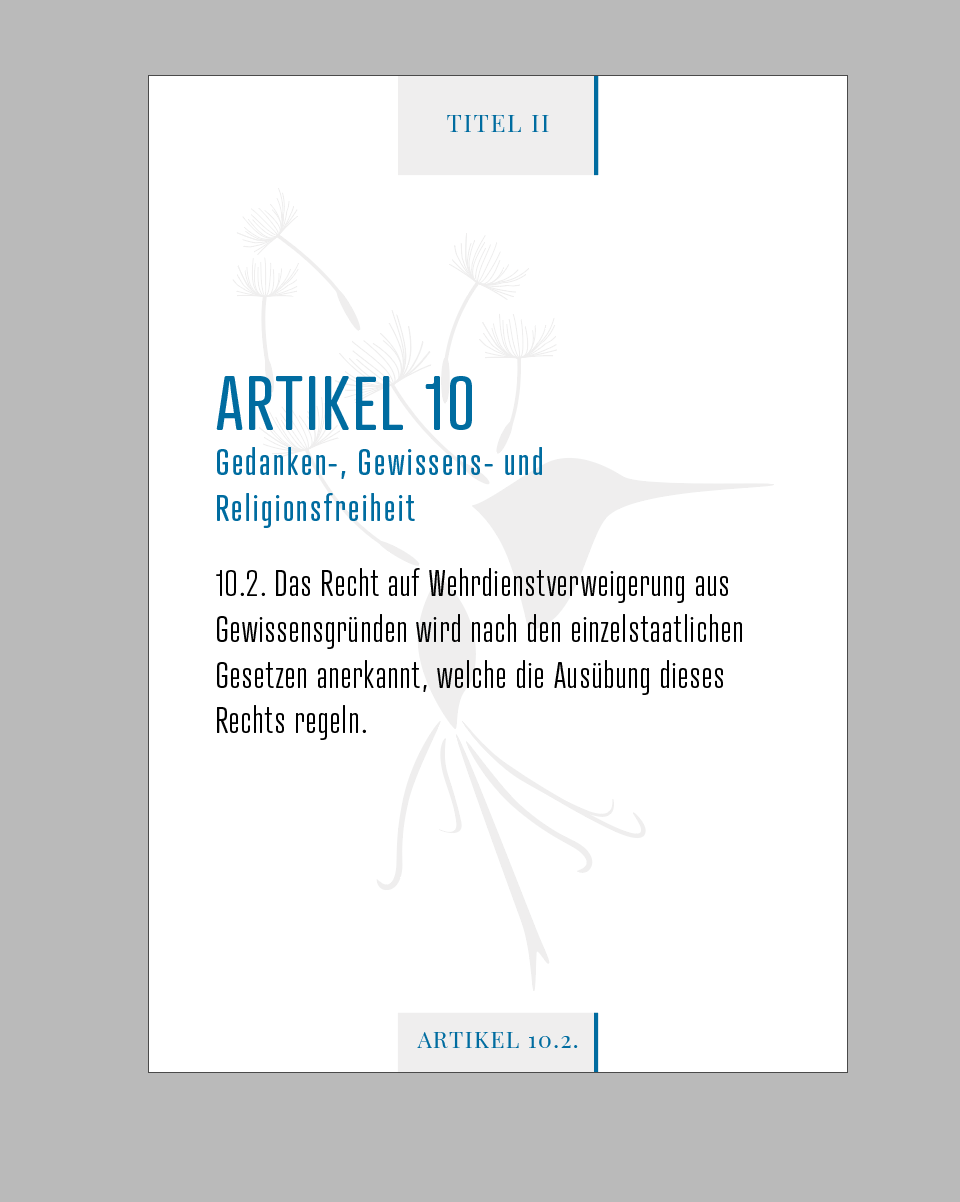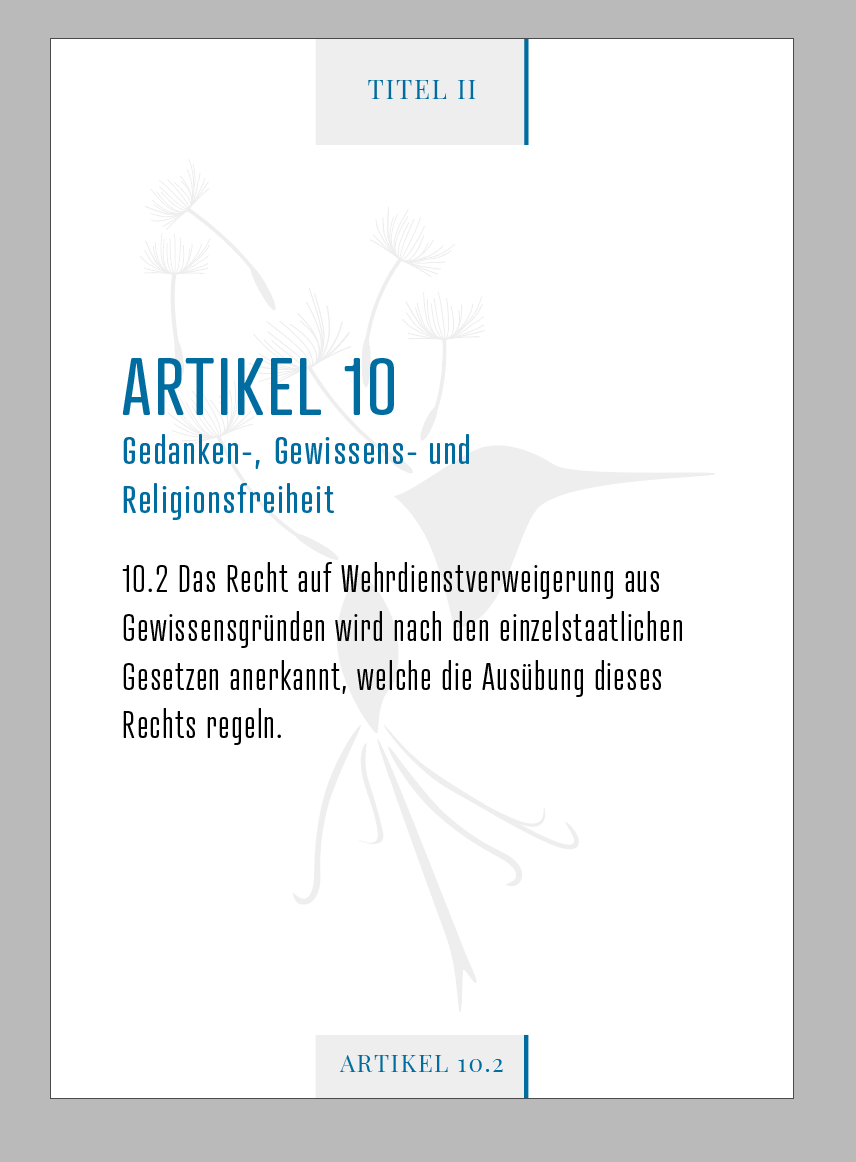
Fonts die miteinander Harmonieren / alle 27 EU Länder beinhalten
dürfte ich euch um Rat bitten. Ich suche zwei Fonts die nicht nur miteinander Harmonieren (Headline, Subline, Fließtext, Fusszeile,) inkl. gute Lesbarkeit (21, 10, 6 Punkt) besitzen, sondern alle Zeichen/Sprachunterstützung der 27 EU-Mitglieder/Länder beinhaltet bzw. unterstützen.
Zielgruppe: Kinder, Jugendliche, Pädagogen, Studenten, Professoren, Sozial-Einrichtungen
Thema: Menschen, Sozial, Politisch, Rechte
Ich finde die größte Herausforderung ist Schriften zu finden, die alle 27 EU-Länder beinhalten.
Diverse Schriftvertriebe haben Standards entwickelt, um in ihren Häusern die Sprachabdeckung einheitlich zu dokumentieren, auch wenn das keine Garantie dafür ist, das auch wirklich alle benötigten Zeichen vorhanden oder ansehlich sind.
W1G steht für World Group 1 und beinhaltet die wichtigsten europäischen Schriftsysteme inkl. Kyrillisch und monotonischen Griechisch, synonym wird WGL4 genutzt.
PE steht für Pan European und sollte alle europäischen Schriftsysteme abdecken inklusive polytonischen Griechisch (was es aber allzu oft doch nicht tut).
Andere Häuser definieren ihre Schriften in STD (Standard), PRO und COM mit aufsteigender Sprachunterstützung und zusätzlichen Feautures.
Wenn Du magst, kannst Du aber gerne hier Deine Ideen mitteilen. Es findet sich so gut wie immer jemand, der Dir weiterhelfen kann. Solltest Du etwas größeres umsetzen müssen und dabei die paarzig Sprachen in Europa benutzen müssen, würde ich doch zu jemanden raten, der sich damit auskennt und auch ein Auge für die Sprachen und ihre schriftlichen Eigentümlichkeiten hat. Die Künstler, die die Schriften entwerfen, beherrschen ja den größten Teil der Sprachen nicht, für die sie Zeichen entwickeln, was dann bei der Zielgruppe manchmal etwas Gänsehaut verursacht (ich denke da an den ungarischen Doppelakut).
Sabrina, die Schriften, die du suchst, sollen ja wahrscheinlich nicht nur die verschiedenen europäischen Sprachen sprechen, sie sollen ja wahrscheinlich auch irgendwie aussehen. Wenn du uns dazu etwas mehr Infos gibst, ist es einfacher, dir was zu raten.
Soll noch einmal jemand etwas sagen Typografie sei einfach und such mal schnell eine andere Schrift.
Welche Schriften habe ich für die Karte verwendet:
TITEL II und ARTIKEL 10.2.  > Playfair Display / Schriftgrad 7PT, Laufweite 65
ARTIKEL 10 > Atrament Regular / Schriftgrad 21PT, Zeilenabstand 24, Laufweite 50
Gedanken-, Gewissens- und Religionsfreiheit: Atrament Regular / 10PT, Zeilenabstand 13, Laufweite 65
Fließtext: Atrament Light/ 10PT, Zeilenabstand 13, Laufweite 40
Ich suche meine Schriften bei Adobe oder bei Fonts.google.com
Zielgruppe sind nicht nur Erwachsene, sondern auch Jugendliche.
Mit Verlaub von einem Nichtdesigner: Die Atrament geht ja gar nicht für den Fließtext. Viel zu fleckig (die w/W), viel zu gedrängelt.
Ich nehme an, Du hast die gewählt, weil sie irgendwie "jugendlich" anmuten könnte?
Aus meiner Arbeit mit Jugendlichen habe ich gelernt, dass diese sehr, sehr schnell merken, wenn sich jemand anbiedern möchte. An erster Stelle seht, unabhängig von der Alters- und Zielgruppe, immer die Leserlichkeit (falls man etwas transportieren möchte, bei Blackmetal-Namen sieht das imo anders aus). Der Fließtext in Atrament wird auf Medien kleiner A5 einfach nur noch matschig sein -- es sei denn, Du hast das schon getestet, ich hab das nur mal eben durch Verkleinerung Deines Bildes simuliert.
Bei "Artikel 10.2" gehört der Punkt nach der 2 weg, also:
1. Ich bin der erste Punkt
1.1 Ich bin der erste Unterpunkt zum ersten Punkt
1.1.1 Ich bin der erste Unterpunkt zum ersten Punkt
Da ist die Aufzählung ja durch den Plural §§ bzw. Artt (sollte nicht mehr verwendet werden) gekennzeichnet. Vorzuziehen ist auch immer die Abkürzung für die Hierarchieebene: Art. 10 Abs 2. Damit sollen Missverständlichkeiten ausgeschlossen werden, immerhin kommt es bei den Juristen auch auf das i-Tüpfelchen an. Mit weiteren Ebenen wäre auch Art. 10 II S. 1 GG möglich.
Bei Gesetzen kenne ich nur diese Schreibweisen:
• Art. 10 Abs. 2 GG
• Art. 10 (2) GG
• Art. 10 II GG
Ohne Punkt* und Komma. (* außer Abk.-Punkt)